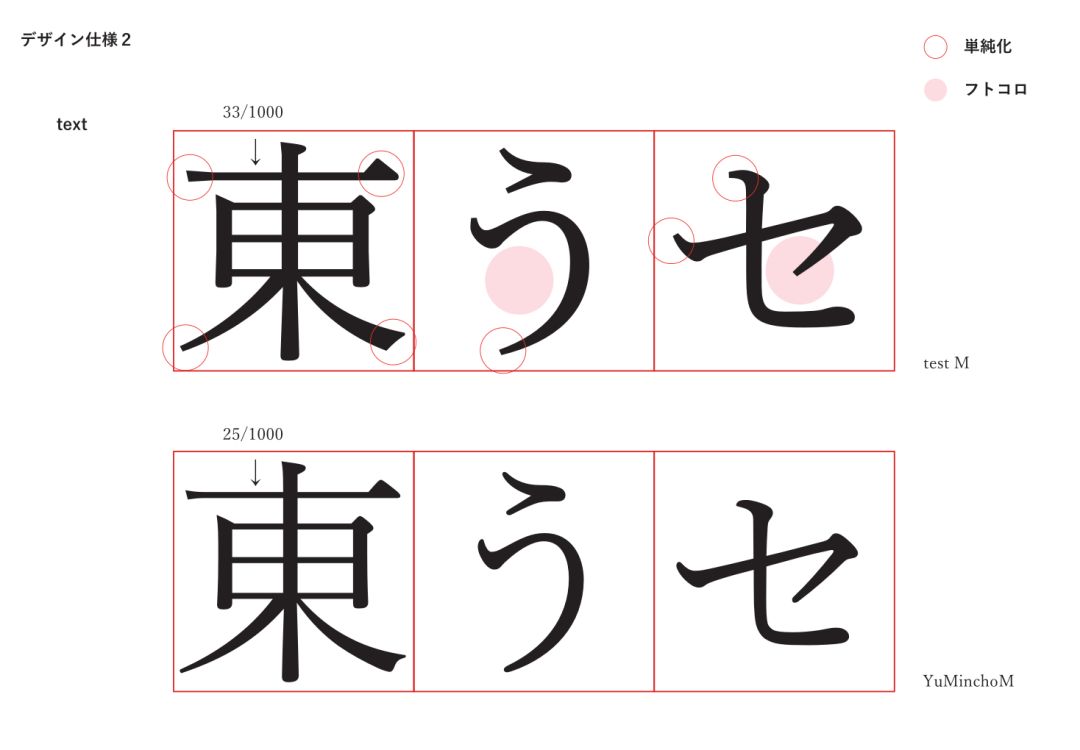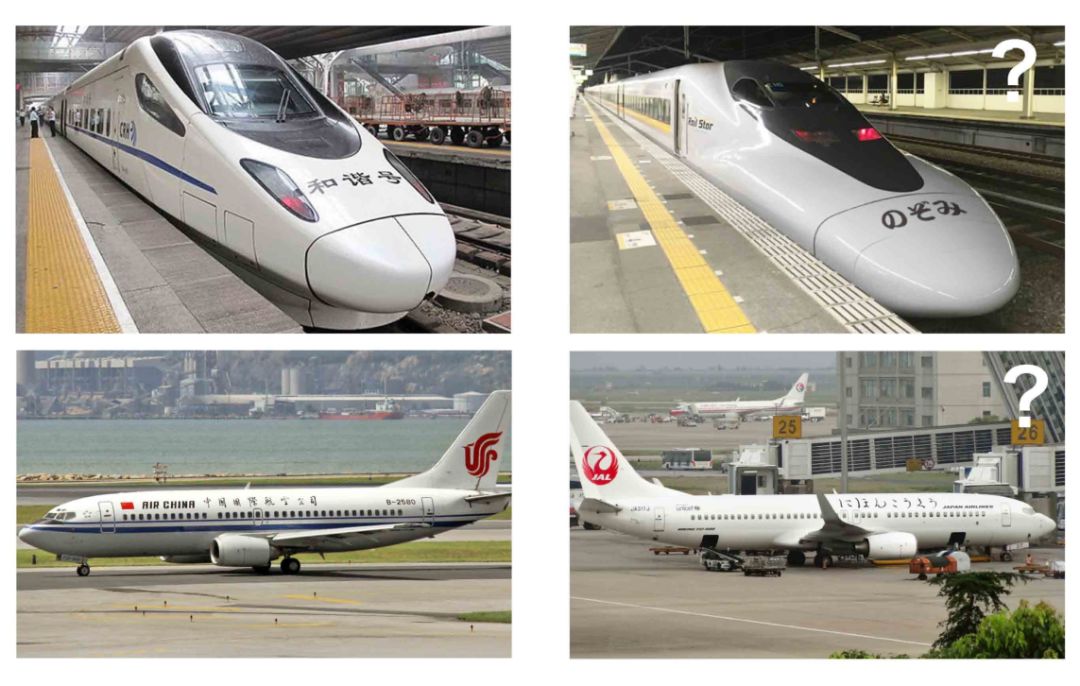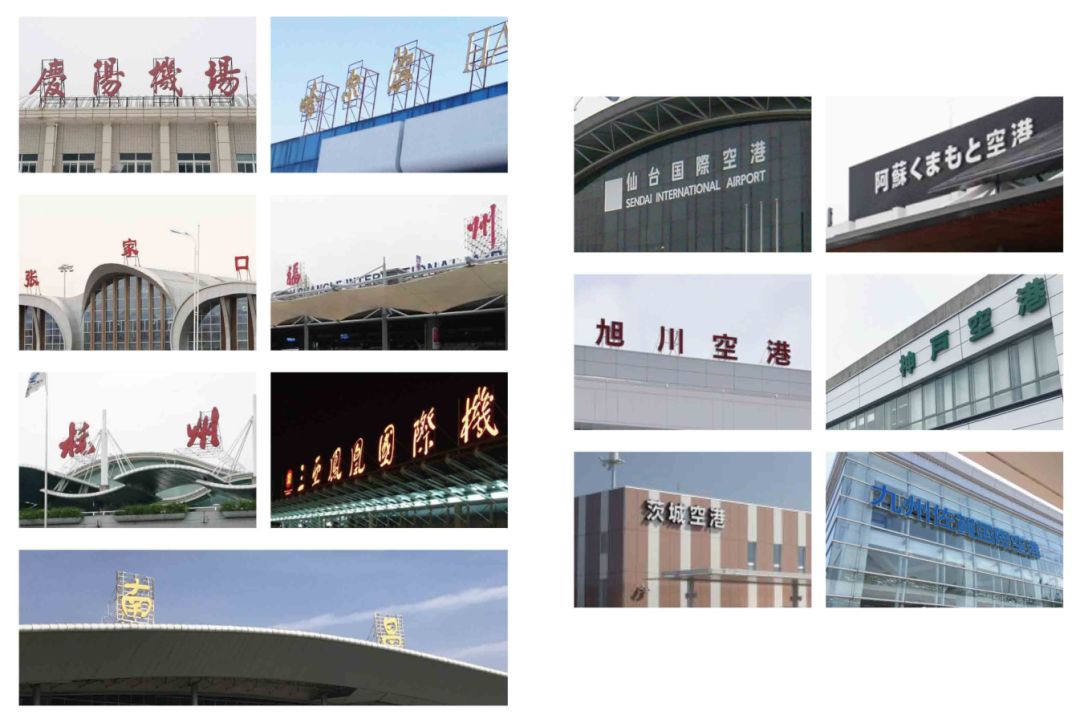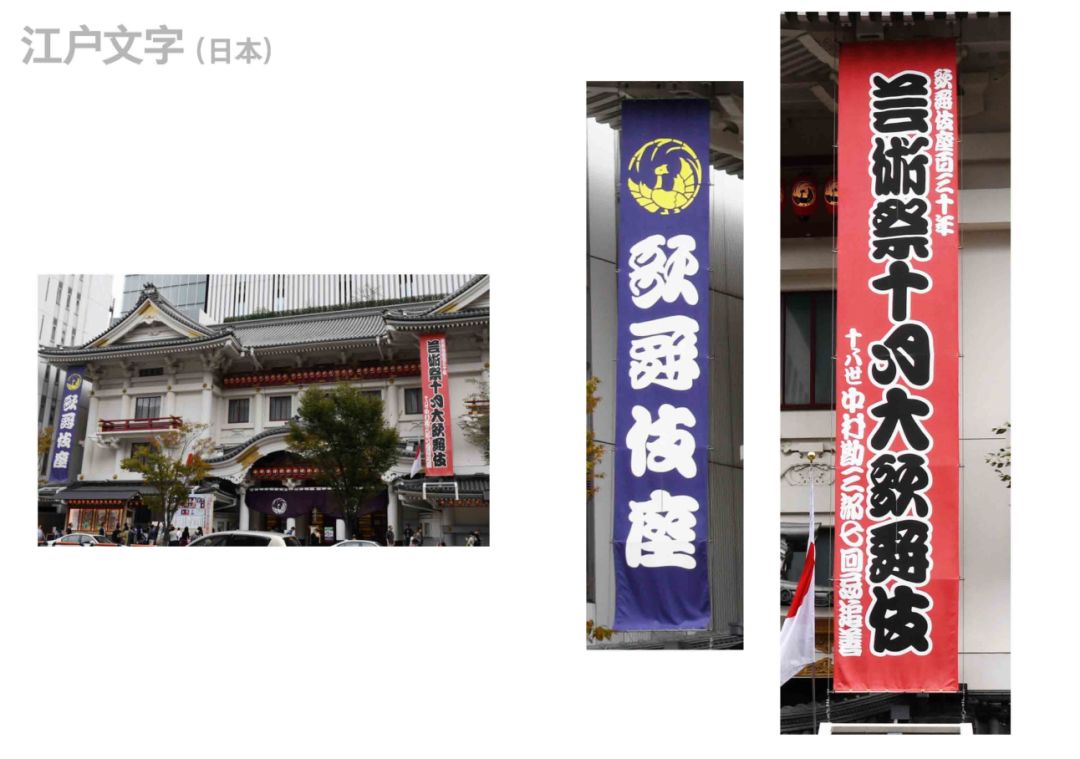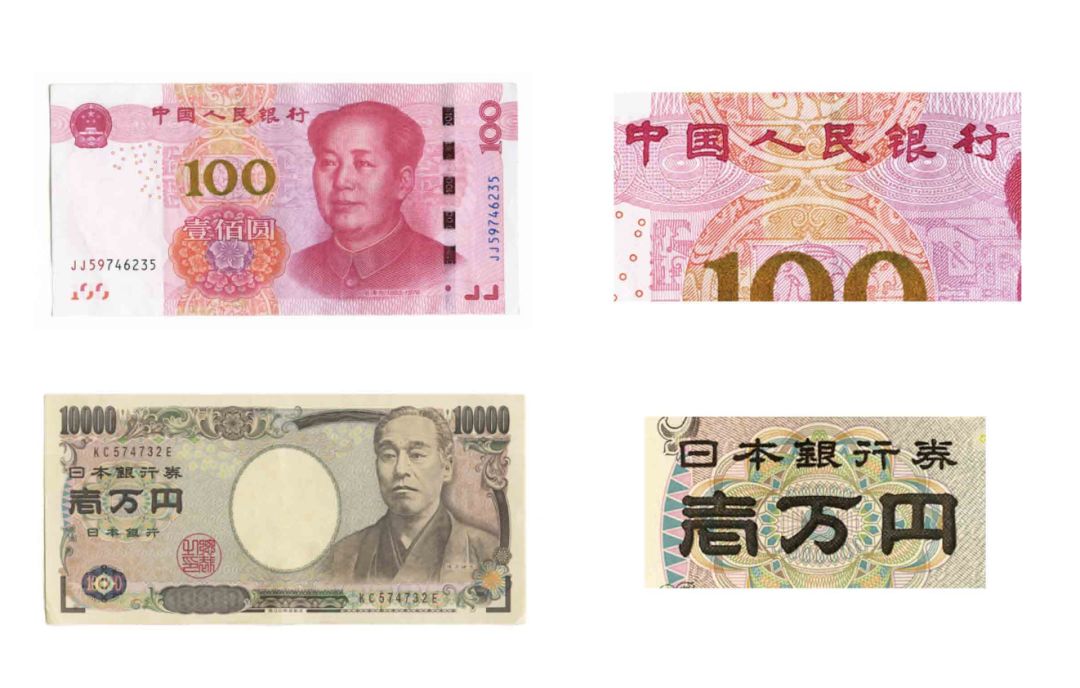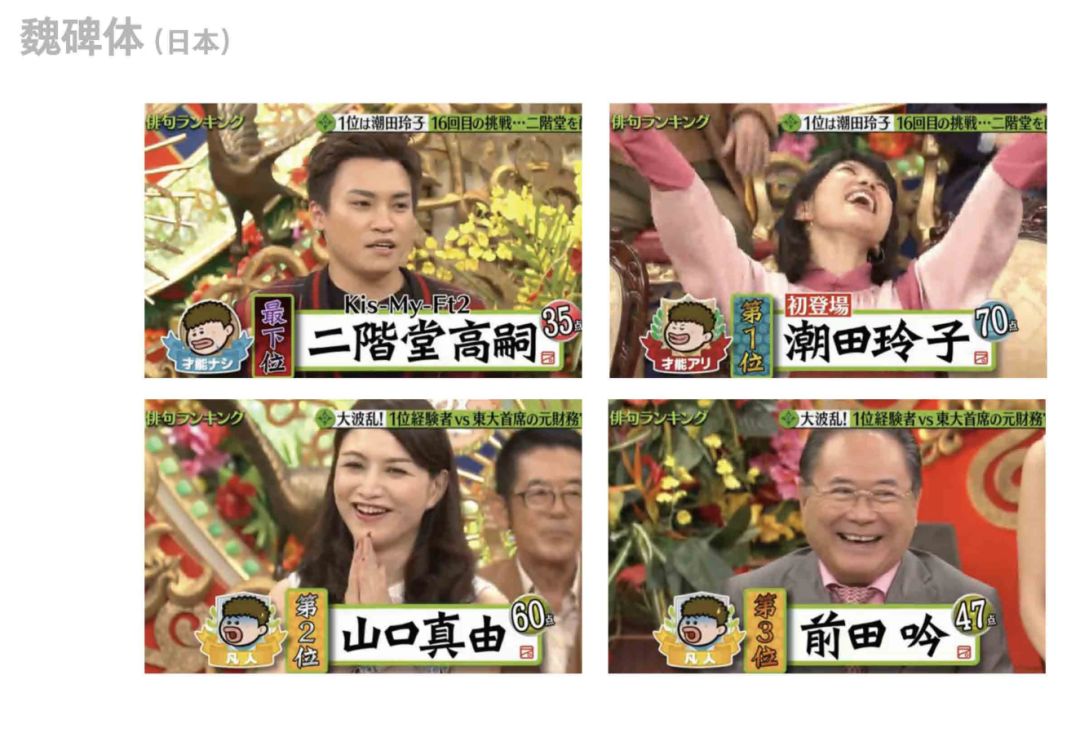
从鸟海修、小矶裕司,看中日字体的设计变化
昨天柚子参加了“字体与时代”主题论坛,见到了字体界的诸多大神,特别是远道而来的鸟海修、小矶裕司老师(穿黑西服白衬衫的就是啦)。
小伙伴们也是很给力,不仅现场座无虚席,直播界面也是人气满满,共有7030人一早就拿着手机守着了(在被窝里学习,也是一种态度)
柚子今天就给你总结一下,本次讲座的精华之处,咳咳~拿好小板凳啦!
字体设计也要为排版考虑
很多人都有这样的困惑,明明字体很好看,但排起来就是不好看,然后就甩锅给设计师,设计师表示冤枉,心想明明是你不会排版好不好?
而鸟海修老师就给我们解答了这个问题,同一款字,可以根据不同的用途,进行微调设计。
比如用作标语的banner,用作陈列展示的display,主标题heading,副标题subheading,还有正文text,图注small。
以text为例,放大看,游明朝体整体加粗了些,笔触末端也调得更直顺,中宫也有所扩大。
而small则在粗度上又加了,笔触末端也有所微调
整体看一下text和small的变化,是不是很明显?
别看这细微的调整,排出来的效果大不一样,左边是调整过的,右边是没调的,哪个看起来更舒服,更易于阅读?
中日字体的应用大不同
下午轮到小矶裕司老师了,可能是看大家刚吃完午饭,有点犯困,他的课题意外地醒脑,都是我们平时经常见到,却很少发现的问题。
比如外出旅行时,在中国总会看见各种字体的招牌,而日本却只有单一的宋体或黑体,有人说这少了一点个性。
但如果你把同样的字体,运用到高铁或飞机上,是不是哪里看起来怪怪的?
其实在日本,你只有在特定的场所,才能看到这种“装饰性”字体,比如表达艺伎的江户文字。
还有在诗歌比赛的节目中,为了配合古风的气氛,运用了魏碑体。
最有意思的是钱币,日元最明显的是隶书的一万円,而人民币最明显的是数字100,这也反映出人民币更注重价值,日元更注重正式感。
小矶裕司老师还开玩笑说,怪不得中国那么流行出门刷手机,而日本却还是很喜欢用现金,哈哈。